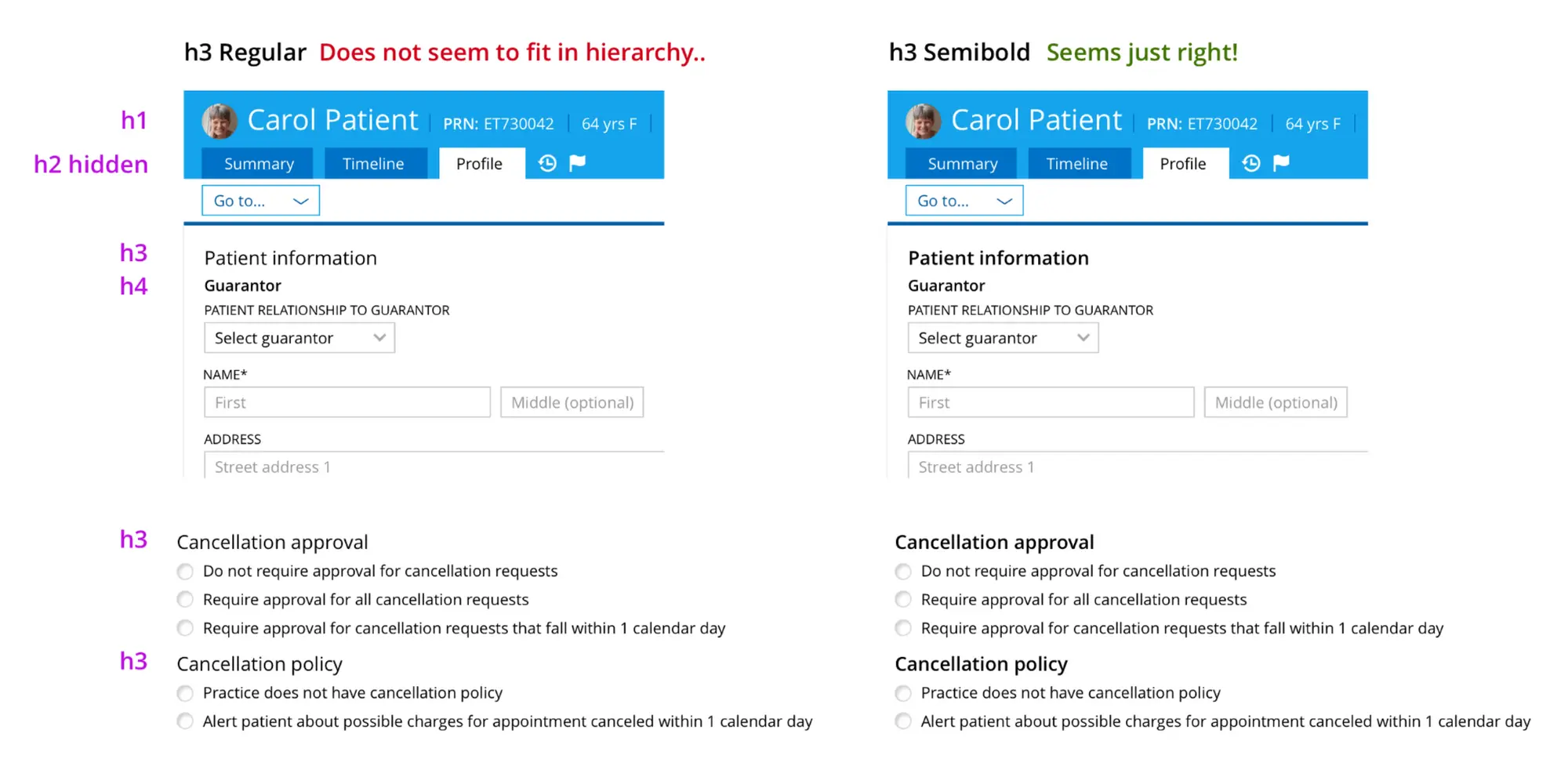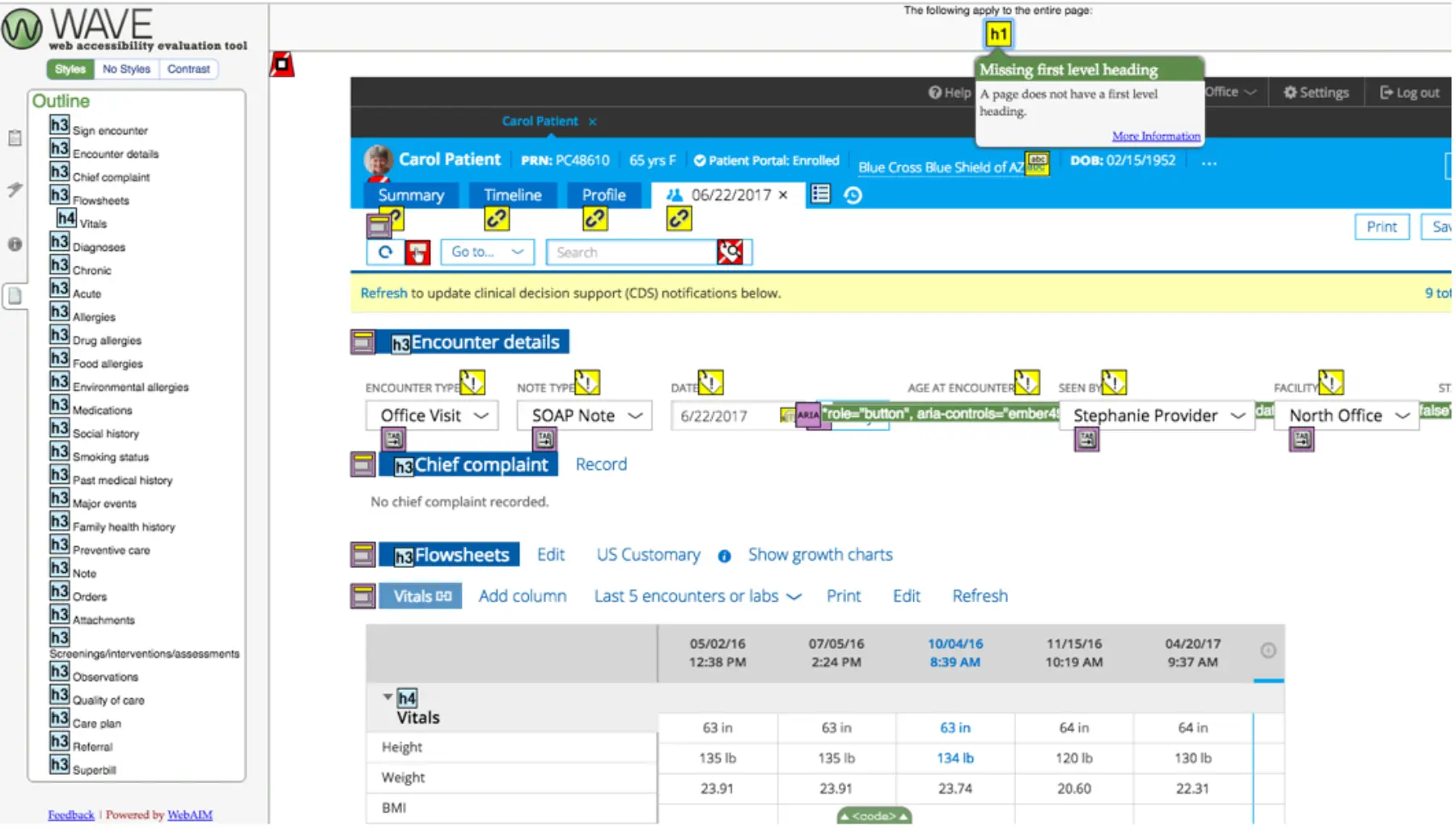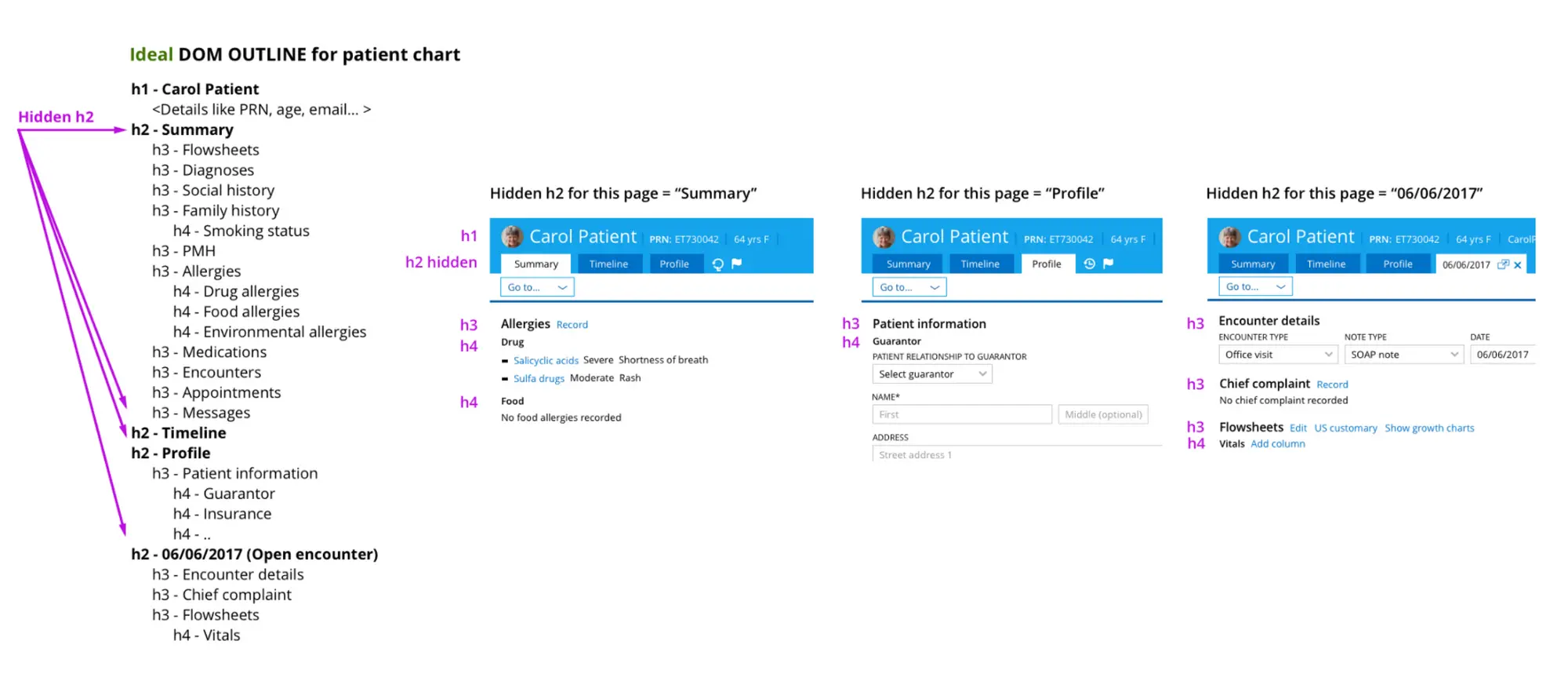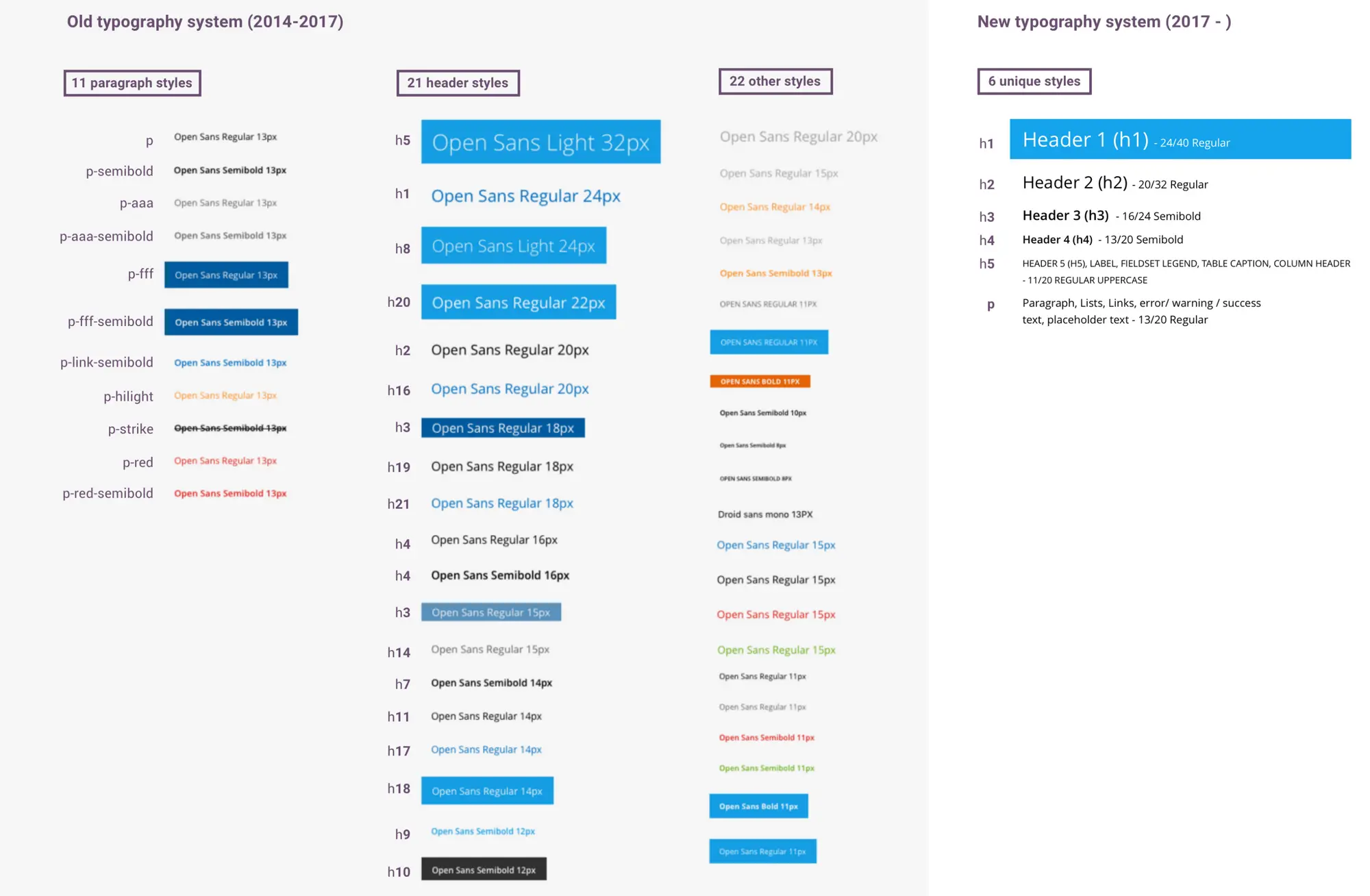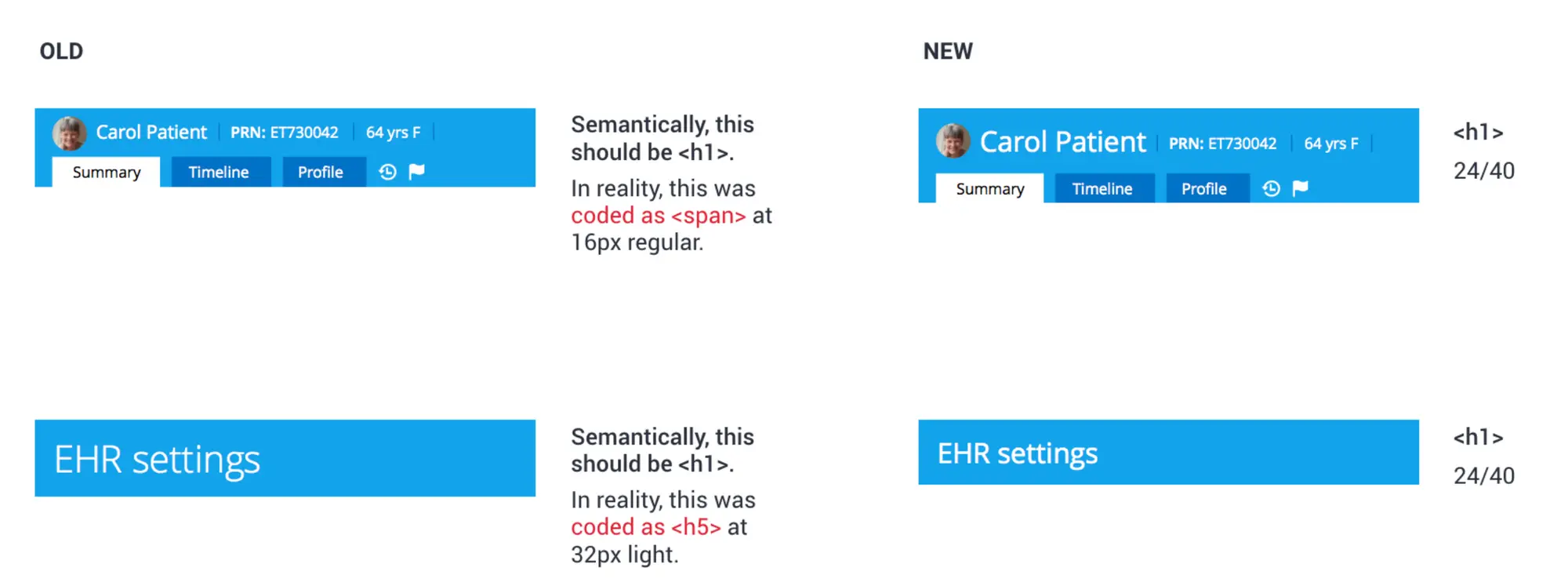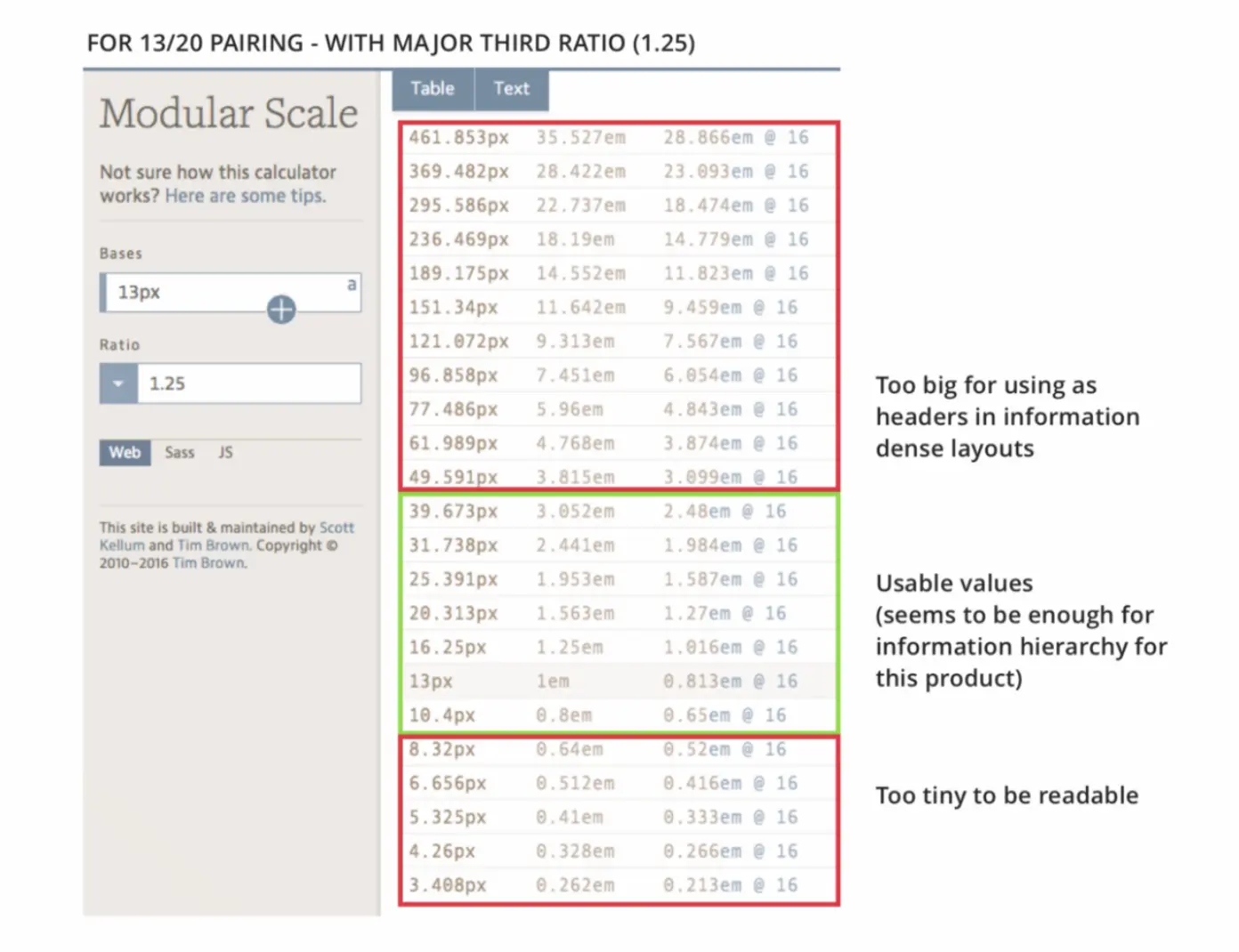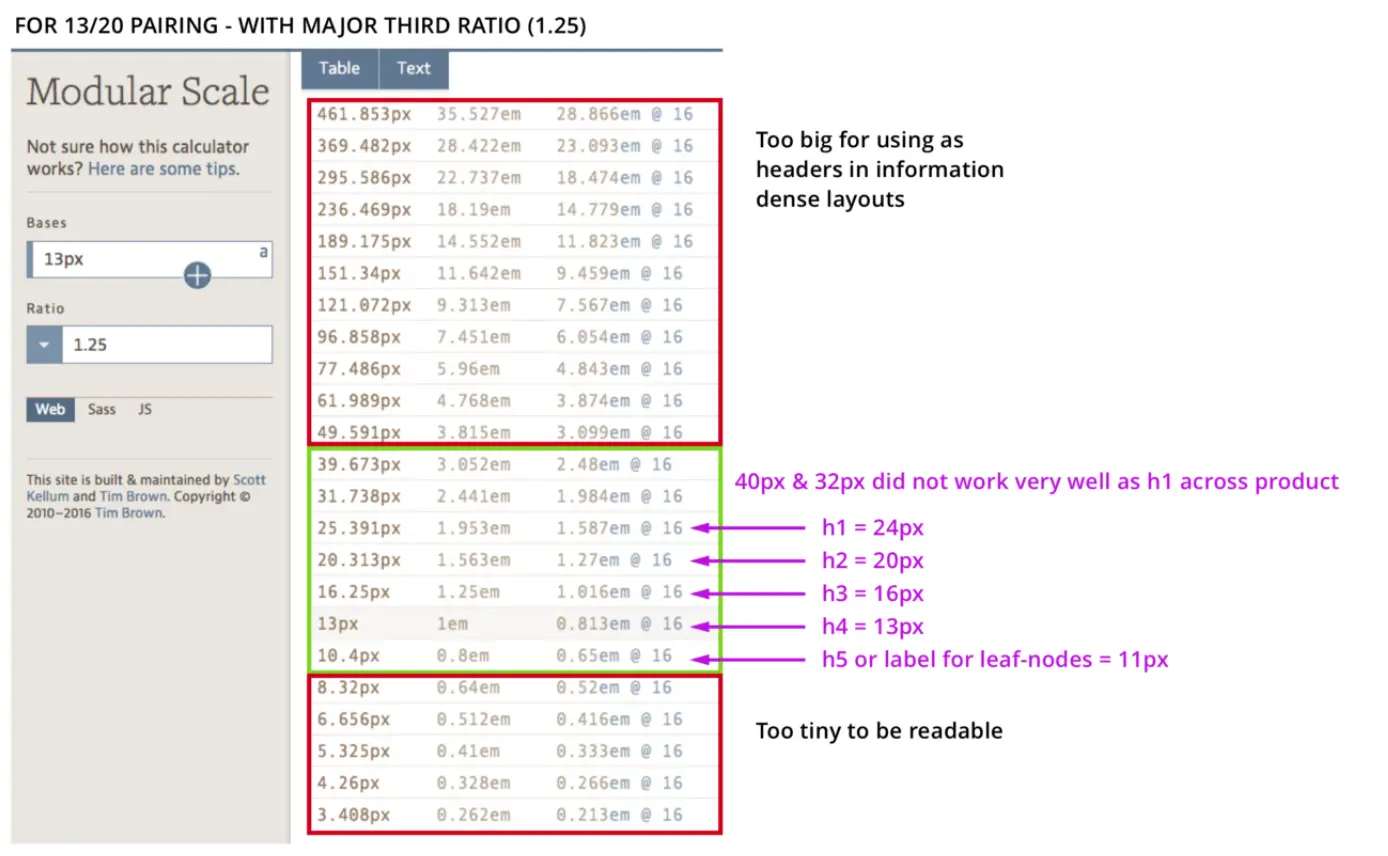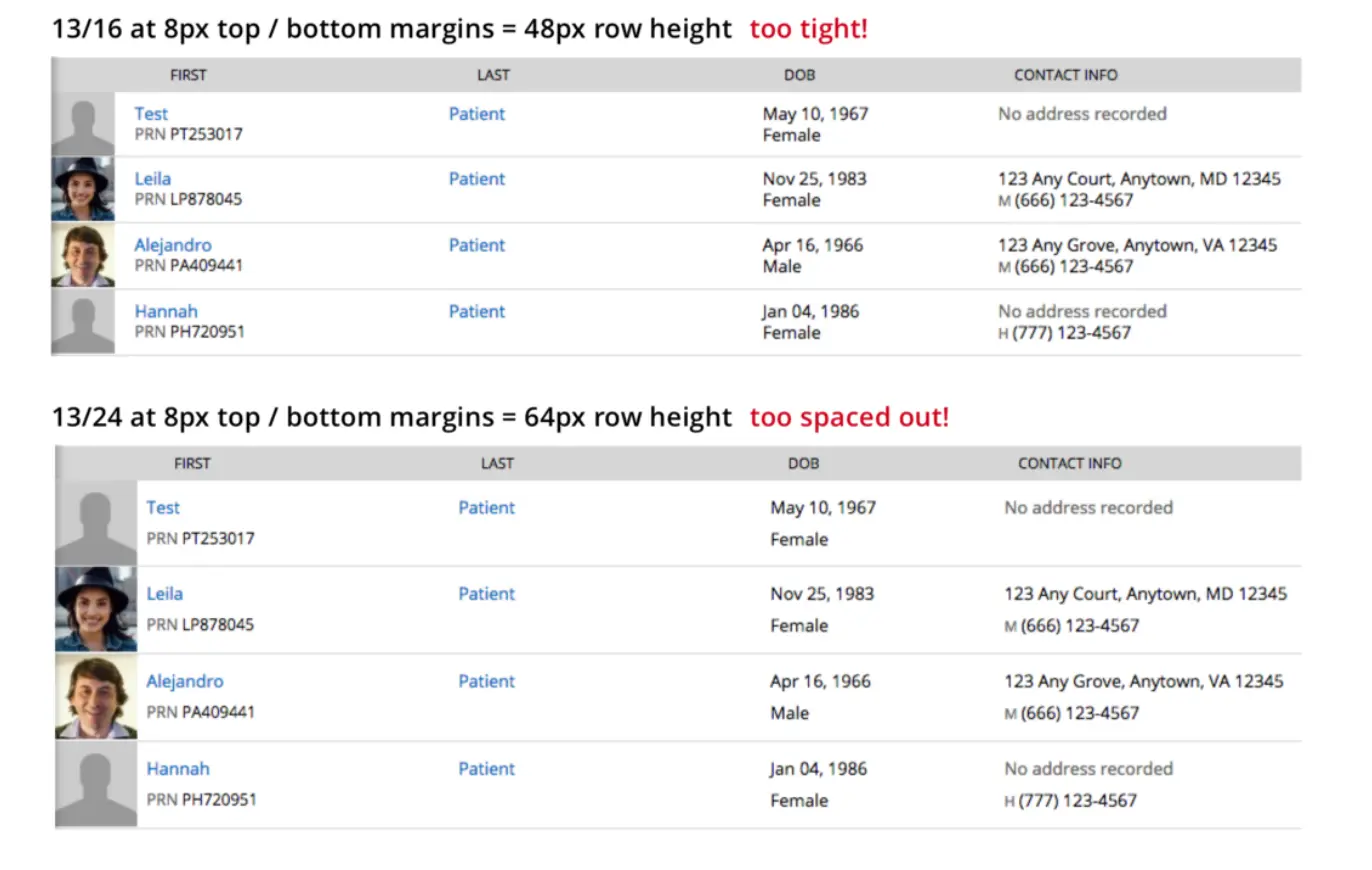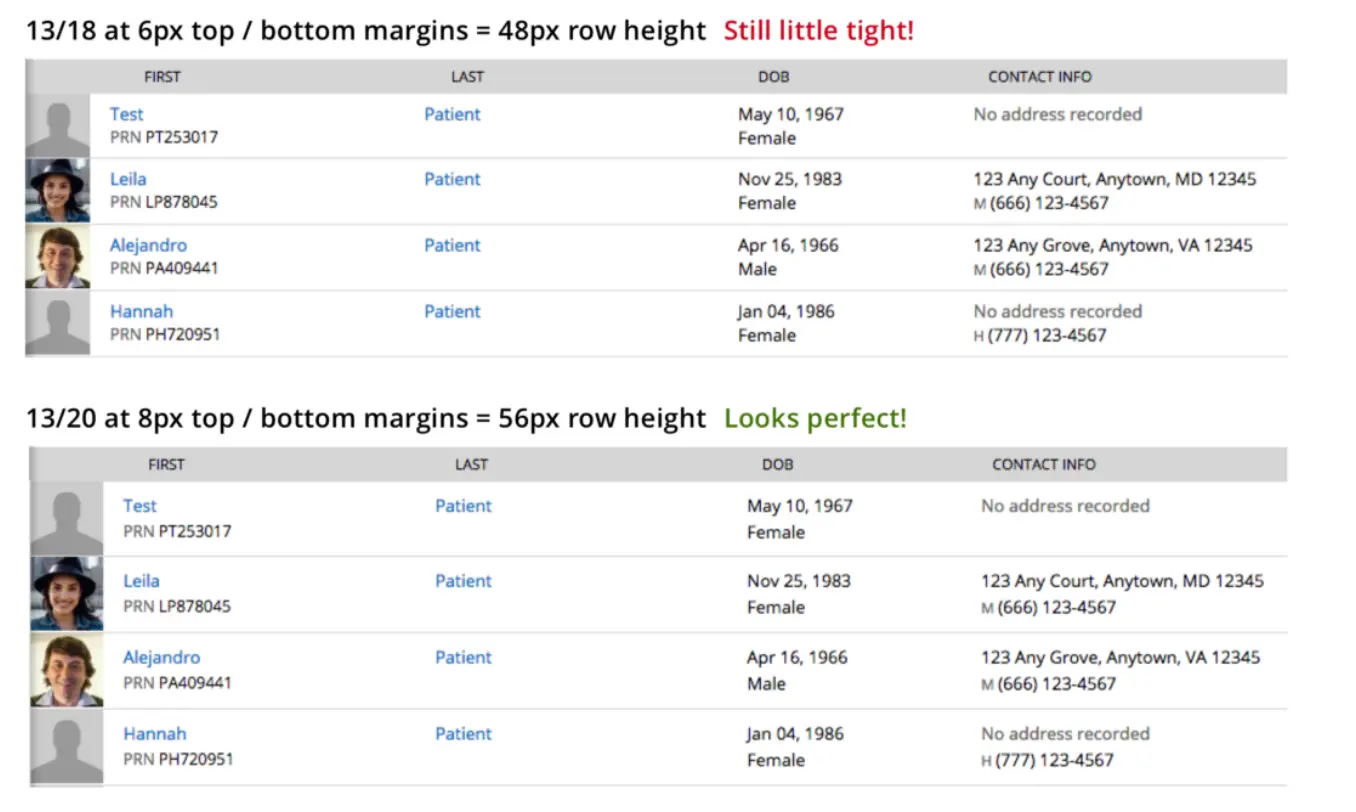
• Notion正在 内测支持中文语言。
• Instagram计划下线创新性交互「 Swipe up links」,计划以链接贴纸的方式替代。但是,这项功能依旧只对粉丝数超过1万或认证用户可用。
• iOS15中,iCloud支持自定义域名,目前仅对开发者开放,如果你是,可以到 这里 尝试。
• Spotify的的 播客付费订阅功能,向美国播客创作者全量开放。
• Netflix的游戏订阅服务,在波兰开启了首轮内测,当前仅限安卓用户参与,且只有两款游戏
• 支付宝推出针对视障用户的「 划一划」密码:用户可在支付宝安全中心提前录入一个图形,需要输入密码时在屏幕划出相应图形即可,解决以往密码被朗读或输入慢等问题。整体方案简单但有效,建议体验。
• 夸克App推出夸克网盘,连续包月会员5元/月、大学生0.99元/月(安卓端)。可以享受文件格式转换、文档扫描、超级视频播放器等智能工具,以及大文件上传、云收藏、云解压等服务。
• 阿里家居应用「躺平」,更新品牌名为「每平每屋」。
✨值得关注的新产品
😈BUD
关注元宇宙概念的小伙伴可能知道这个产品,从版本记录看,已经推出相当长时间了,所以内部设施和内容相当完善。体验下来非常惊讶里面的用户的创造力,建议关注。同时这里简单分享下,作者接触到的现在市面上对元宇宙的理解和派别:
• 由硬件支撑,从体验上突破现实和虚拟边界的,以facebook为代表,应用是上期我们提过的 Horizon Workrooms
• 从模式创新,将3D技术应用到App中,典型场景是build个人作品,每个人形成自我的「元宇宙」,以Roblox为代表,Bud更接近这个解法
• 由概念包装,线上体验是线下的一一映射,以 Gather 为代表
• 由Crypto为支持,基于区块链的技术
💳dot. cards
dot.是Linktree的实体版,两者解决的需求有点类似,社交媒体往往会屏蔽竞品的跳转链接,如果要向外引流,就需要依赖其他服务。linktree提供的就是聚合社媒账号的功能,而dot.提供的实体版方案,更偏商务场景。
👀UI里的字体系统(Typographic System)是什么?
前言:上一篇提到了推特团队新字体Chirp上线后遇到的一系列显示问题,然而对于大部分设计师来说,还不至于要为APP设计一款新的显示字体。那么如何将已有的字体在产品中运用好?
这系列文章来自Medium,Priyanka Godbole(Facebook的product designer)记录的为一个健康信息网站重新制作设计规范的过程,网站涉及大量可视化数据,是研究字体排版的好样本。以下不是完全直白翻译,而是参合了我个人的一些思考和简化,附上 原文传送门。
改版第一步:整理现有产品的字体语义层级和视觉层级
如果你是为一个现有产品进行设计优化,首先要做的就是整理现有的字体层级。作者使用了Chrome插件审查原有的EHR网站,使用假数据填充丰富网页查看所有现有字体样式。作者发现原来网页居然有多达51种样式(包括颜色和字重在内)。可以想象如此混乱的样式会给设计师和工程师在实际使用中带来很大的负担和困扰。
仔细看上表,作者最终把字体变量缩减到了6种,5种header和1种正文字体(段落、列表、链接、提醒、占位文字)没有将颜色纳入变量是因为正文字体只有在作为链接是蓝色,错误提醒是红色,占位文字是灰色,其它情况下都是黑色。而标题大多数情况下都保持一个字重,特殊用法再特殊定义)
再来看语义审查,在老的设计中,每个页面页头是H5字号,然后页面内使用了H3,但H3下内容里的表格却用了H4。理想地说,是不应该发生这样的跳级的。
在视觉层级上,我们主要关注字体的字号和字重。可以看到整理出来的老系统里多达9种header,然而产品并不需要如此复杂的信息层级,这显然是个欠缺考虑的决定。特别是对于APP来说,每个页面的信息量更加少,遵循一个步骤做一件事的原则,我们应该仔细考虑页面的信息重点给予突出,而不是给每一个小细节都加上粗体。
改版第二步:从正文字号开始
在了解现有问题后,作者从正文字体开始了这次字体系统重设计,因为这个字号在网页里表现得不错,阅读体验也挺好,所以以它作为一个良好开始。在网页上,10pt是最小可读字号,约等于13px。我比较赞成从正文字号开始设计字体系统是因为它出现频率最高,而在APP上由于手机分辨率越来越高,即使是10pt英文字体也是看的清,但是要尽量避免这种在可读性上打擦边球的行为,而且随着屏幕变大和考虑到适老化,正文字体建议不要低于14pt。许多主流阅读类APP正文都在15~16pt左右。
改版第三步:为基础字号制定行高
作者通过填充数据,反复体验得到了13号字的合适行距20px,测试数据基于8px/4px的倍数。
此时20px行距并不满足作者原先制定的8px的网格系统(网格系统是为了保证UI间距上的视觉延续性)但是作者却没有因此改变策略。对于更小,需要紧凑间距的字体系统、icon采用4px作为基本距离单位,而整体模块布局则采用8px作为基本距离单位,提供更可辨识的UI层次。说到底,设计系统是为了减少视觉不统一和更简单的执行。
合适的行高需要通过多次体验来确定,不同平台上的体感也不一样,网页字体一般比APP要有更大的行高(考虑到阅读距离和屏幕大小)
第四步:从正文字号通过比率缩放得到其它字号
基础知识:
比率缩放工具 - Tim Brown’s Modular Scale: https://www.modularscale.com/
Rem - 相对单位比例,例如网页默认1rem=16px,那么1.5rem= 24px
作者通过20/13得到目前字体系统比率1.538,缩放后发现由于比率过大导致字号分散,可用字号太少
为了保证20px依旧在新的比率上,选择了1.538折半后的1.25比率,这样既能维持行高垂直空间上的节奏又能得到一个更为紧凑的字号区间。
第五步:重新梳理页面语义
基础知识:
Header - HTML中的标签,用于定义文档的页眉(介绍信息)
在从上一步得到有效的字体中选取合适的实际应用到页面中,在旧官网上,每个页面页头是不统一的。有些是16px <header 1>,有些却是32px <header 5>,为了连贯使用header 1,作者统一制定了24px <header 1>作为每个页面标题。
根据信息复杂程度决定我们需要多少种header,值得注意,即使是EHR里信息密度最大的一个页面也没有使用超过5种header,普通的页面3种header就够了
第七步:为字体系统里的所有字号制定行距
通过最初的20/13得出的1.538比率等比例得到每个字号的行距,通过网格系统筛选出合适数值。(下图)
第九步:将字体系统运用到网页页面上
基础知识:
HTML DOM :文档对象模型 - 当页面被加载时,浏览器会创建页面的文档对象模型(document object model),是中立于平台和语言的接口。
因为这次涉及我不熟悉的代码知识,建议感兴趣的直接查看原文。总之就是借助DOM,保证页面的语义和视觉上的连续性。
总结
遵循以上过程
• 你可以轻松排除那些冗余不重要的视觉信息
• 你团队里的设计师会知道如何去使用字体,不再存在认知混淆
• 同理,工程师通过已有标准能加速开发进程,而不用一遍遍去审查设计稿
对我来说:
在从0到1做一个产品的时候,设计师每天需要做许多决策,间距多宽,字号多大,按钮多高等等,这些细小零碎的决策最终会决定整个APP的质感。这些决策并非拍拍脑袋就能做出,结合理论知识可以帮助我们更快地做出决策。
同样,当APP已经到了稳定迭代的阶段,设计师一定要尽早系统地去构造产品的设计系统,不然问题会随着时间积累,渗透到每一个页面,UI上给人参差不齐的感觉,同时还会影响迭代的设计效率。
制定一个完善的设计系统还能让后来参与的设计师能很快接手工作,以及节约开发和测试的时间。